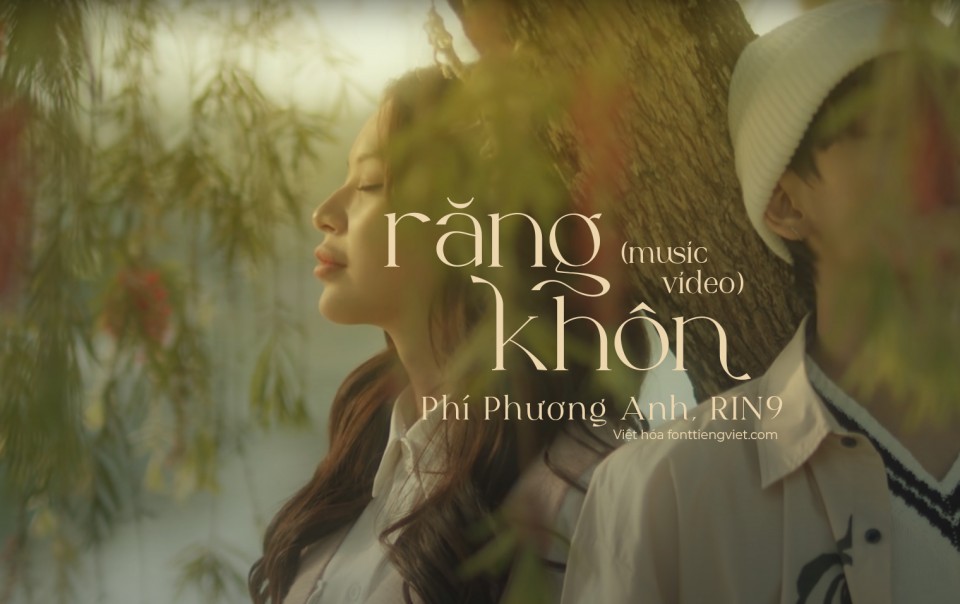
Font việt hòa 1FTV dùng cho MV ca nhạc 1
Giới thiệu về Font việt hòa 1FTV dùng cho MV ca nhạc 1
Trong nghệ thuật sản xuất video âm nhạc hiện đại, việc lựa chọn Font Miễn Phí phù hợp đóng vai trò then chốt để truyền tải cảm xúc của bài hát. Font việt hòa 1FTV dùng cho MV ca nhạc 1 là một bộ phông chữ được thiết kế chuyên biệt cho các dự án sáng tạo hình ảnh. Với các đường nét thanh thoát nhưng không kém phần mạnh mẽ, bộ font này giúp các editor dễ dàng tạo ra những khung hình lyric ấn tượng. Việc sử dụng đúng font chữ không chỉ giúp khán giả dễ dàng theo dõi lời bài hát mà còn nâng tầm thẩm mỹ cho toàn bộ tác phẩm nghệ thuật của bạn. Bộ font 1FTV này đã được tối ưu hóa hoàn toàn cho tiếng Việt, giúp loại bỏ các lỗi hiển thị dấu phổ biến, đảm bảo tính chuyên nghiệp cao nhất cho mọi khung hình.
Ưu điểm nổi bật của Font việt hòa 1FTV
Đặc điểm lớn nhất của Font việt hòa 1FTV dùng cho MV ca nhạc 1 chính là sự linh hoạt trong nhiều phong cách âm nhạc khác nhau. Cho dù bạn đang thực hiện một bản Ballad nhẹ nhàng, sâu lắng hay một bản nhạc EDM sôi động, bộ font này vẫn có khả năng thích ứng hoàn hảo. Các ký tự được chăm chút kỹ lưỡng về khoảng cách, giúp việc đọc văn bản trên màn hình trở nên dễ chịu hơn ngay cả ở độ phân giải thấp. Ngoài ra, phông chữ này còn hỗ trợ đầy đủ các ký tự đặc biệt, giúp các nhà làm phim thoải mái sáng tạo các hiệu ứng chuyển động mà không sợ bị giới hạn về kỹ thuật trình bày văn bản.
Cách ứng dụng Font việt hòa 1FTV dùng cho MV ca nhạc 1 hiệu quả
Để khai thác tối đa sức mạnh của Font việt hòa 1FTV dùng cho MV ca nhạc 1, người dùng nên chú ý đến sự tương phản giữa chữ và nền. Trong các MV ca nhạc, phần chữ thường được đặt ở vị trí trung tâm hoặc phía dưới màn hình. Bạn có thể kết hợp thêm các hiệu ứng như đổ bóng nhẹ hoặc viền chữ để làm nổi bật thông điệp. Việc sử dụng font này cho phần tiêu đề bài hát ở đầu video cũng là một lựa chọn thông minh để tạo ấn tượng thị giác ngay từ giây đầu tiên. Ngoài ra, bộ font này cũng rất phù hợp để làm các poster quảng bá MV trên mạng xã hội nhờ tính hiện đại và sang trọng vốn có.
Lưu ý khi thiết kế phông chữ cho video
Khi sử dụng Font việt hòa 1FTV dùng cho MV ca nhạc 1, bạn không nên sử dụng quá nhiều kiểu chữ khác nhau trong cùng một phân cảnh để tránh gây rối mắt. Sự nhất quán là chìa khóa tạo nên một sản phẩm chuyên nghiệp. Bạn có thể thay đổi kích thước hoặc độ đậm nhạt của font để tạo ra sự phân cấp thông tin rõ ràng giữa tên ca sĩ và lời bài hát. Đặc biệt, hãy kiểm tra kỹ tính hiển thị trên các thiết bị di động vì đây là nơi phần lớn khán giả sẽ tiếp cận MV của bạn. Một phông chữ đẹp là phông chữ có thể đọc rõ ràng ở mọi kích thước màn hình mà vẫn giữ được cái hồn của thiết kế ban đầu.
Kết luận về bộ Font việt hòa 1FTV dùng cho MV ca nhạc 1